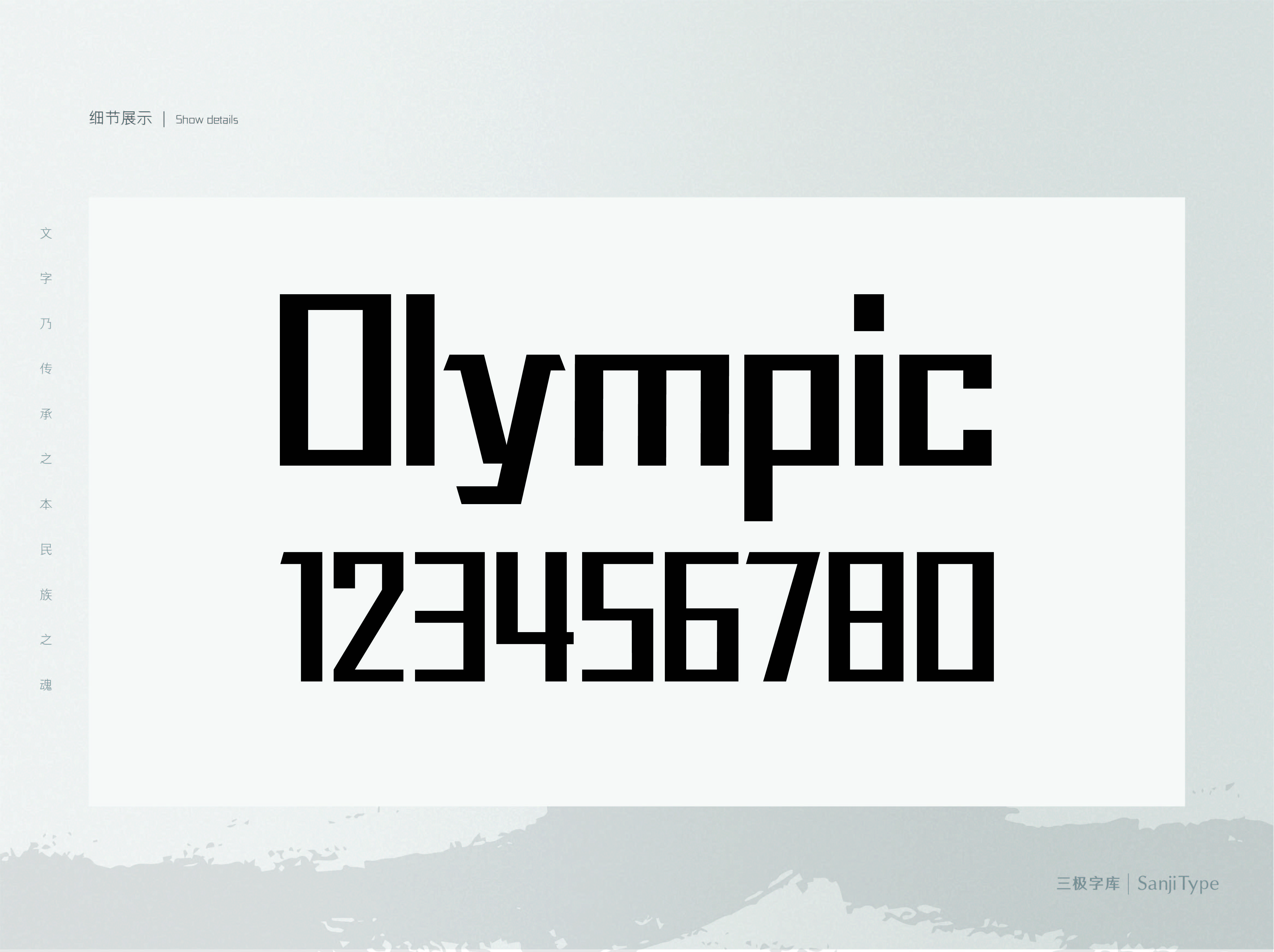
三极谌利军力量体家族
三极谌利军力量体 纤细
三极谌利军力量体
三极谌利军力量体 中粗
三极谌利军力量体 粗
三极谌利军力量体 超粗
三极谌利军力量体 细
曾南 李文浩 罗碧霞 蔡建文
黑体
创作灵感来自于奥运体育精神,整体充满稳定感和力量感。字形方正棱角分明,结构严谨,重心稳定,布白均匀。撇、捺笔画镜像对称,字形充满整个字面框。三极谌利军力量体适用于商业品牌的广告、产品包装设计、影视作品,界面设计等,能够为画面增强力量感。